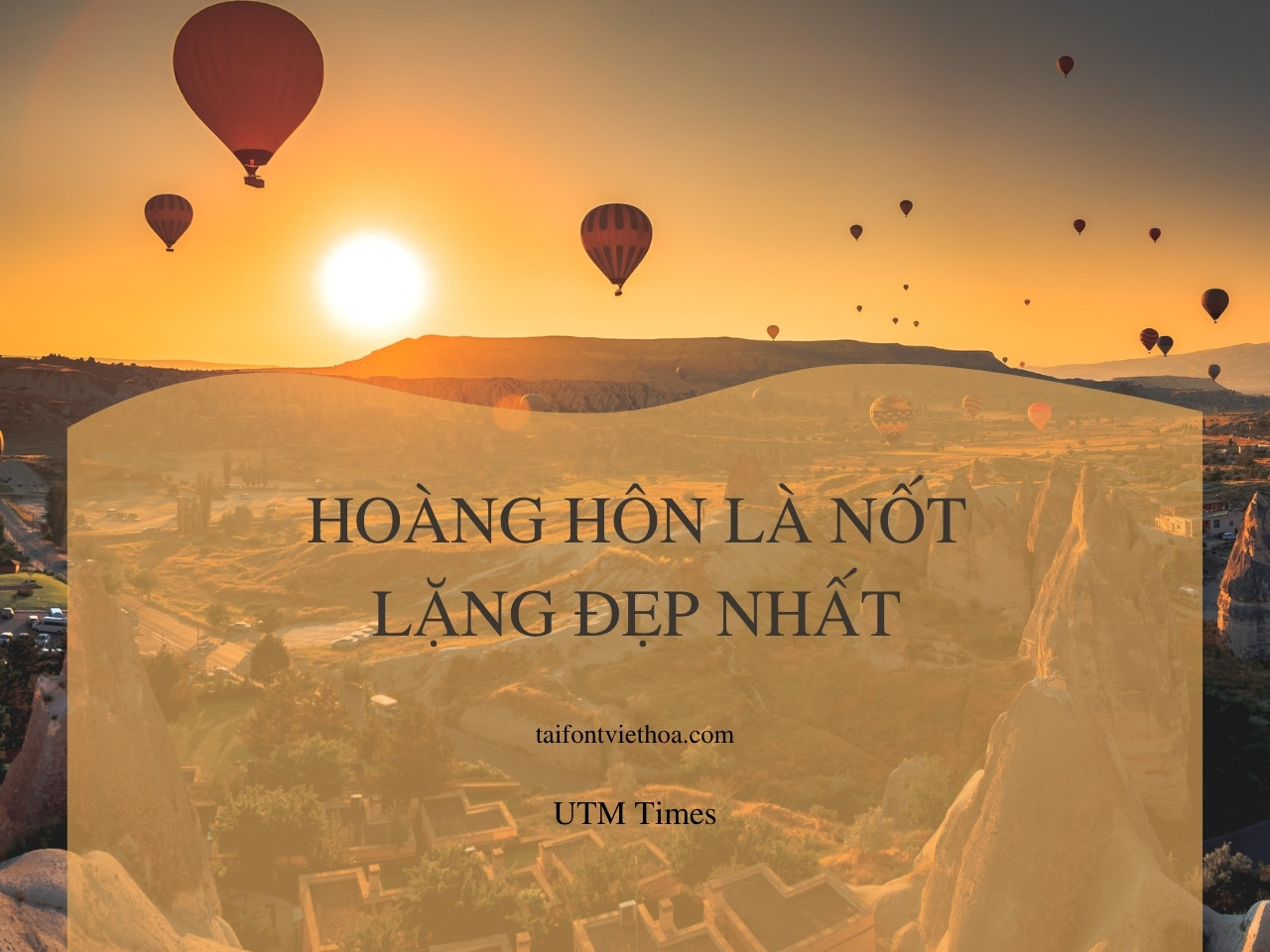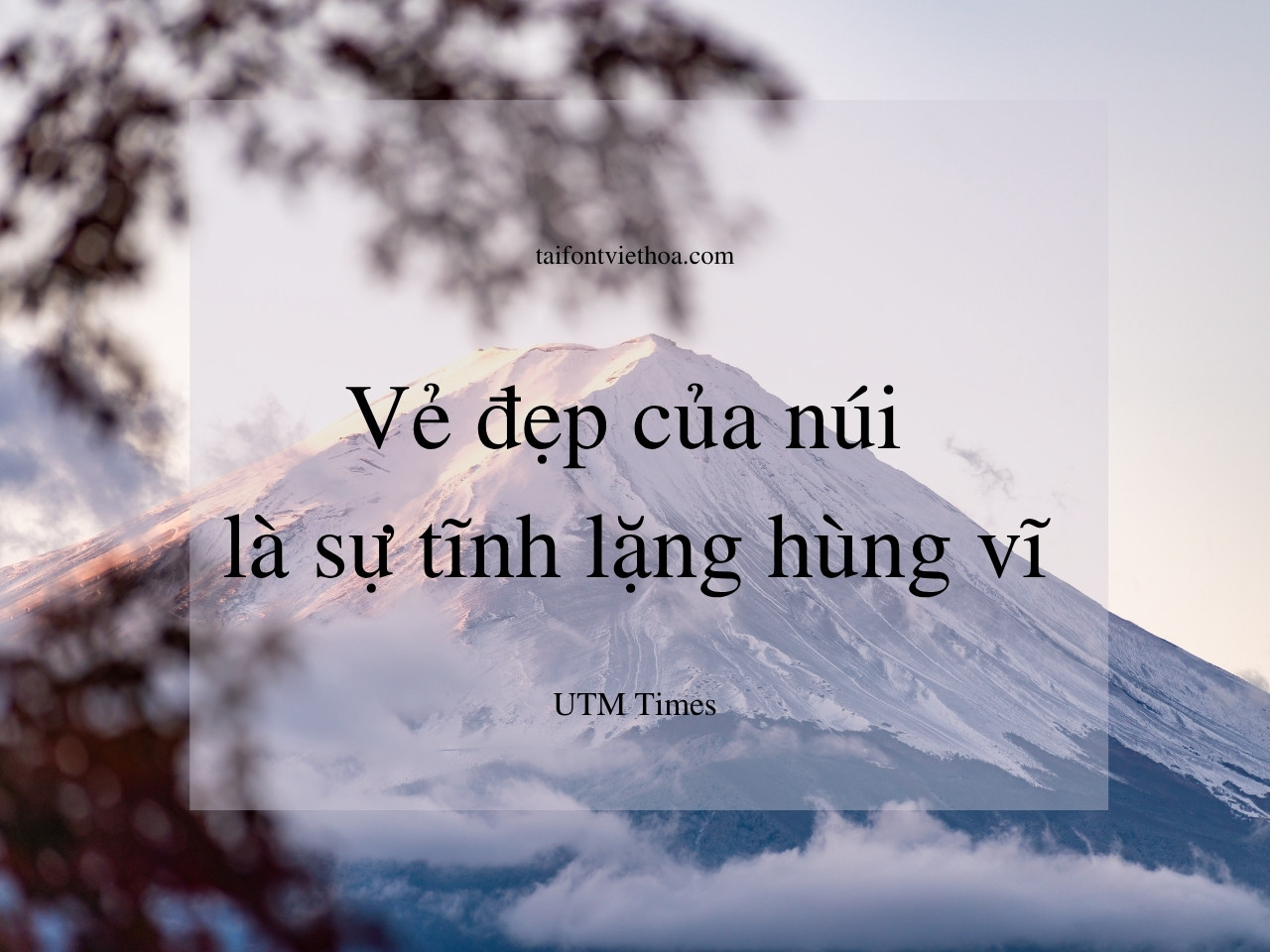
Font việt hóa UTM Times đầy đủ
Giới thiệu về font UTM Times Trọn Bộ – Bộ font serif kinh điển và đa dụng
UTM Times Trọn Bộ là phiên bản Việt hóa của bộ font Times – một bộ sưu tập font serif nổi tiếng và được sử dụng rộng rãi trên toàn thế giới. Bộ font Times nổi bật với thiết kế chữ có chân (serif) thanh lịch, dễ đọc và mang tính truyền thống, phù hợp cho nhiều mục đích thiết kế khác nhau từ in ấn đến truyền thông kỹ thuật số. Phiên bản Việt hóa đã được hoàn thiện để hỗ trợ đầy đủ tiếng Việt cùng hơn 200 ngôn ngữ khác, giúp mở rộng phạm vi sử dụng trong các dự án thiết kế chuyên nghiệp và đa dạng.
Font UTM Times Trọn Bộ được taifontviethoa.com lựa chọn và sưu tầm kỹ lưỡng nhằm phục vụ cộng đồng thiết kế Việt Nam. Phiên bản Việt hóa giữ nguyên nét truyền thống và chuyên nghiệp của bộ font gốc, đồng thời tối ưu khả năng hiển thị tiếng Việt, rất phù hợp cho các dự án sách, tạp chí, báo chí, thương hiệu và truyền thông đa phương tiện.
Giới thiệu về font UTM Times Trọn Bộ – Bộ font serif kinh điển và đa dụng
Đặc điểm thiết kế và ứng dụng của UTM Times Trọn Bộ
UTM Times Trọn Bộ bao gồm nhiều biến thể trọng lượng và phong cách, giúp các nhà thiết kế dễ dàng lựa chọn và kết hợp trong nhiều bối cảnh khác nhau. Bộ font có cấu trúc serif với các nét chân chữ sắc nét, mềm mại và cân đối, mang lại cảm giác dễ đọc, trang nhã và chuyên nghiệp. Thiết kế font phù hợp cho cả tiêu đề và nội dung chi tiết.
Font thích hợp sử dụng trong thiết kế sách, tạp chí, báo chí, nhận diện thương hiệu, quảng cáo, bao bì sản phẩm và các dự án truyền thông đa phương tiện. Các ngành nghề phù hợp gồm: xuất bản, giáo dục, báo chí, nghệ thuật và thiết kế nội thất.